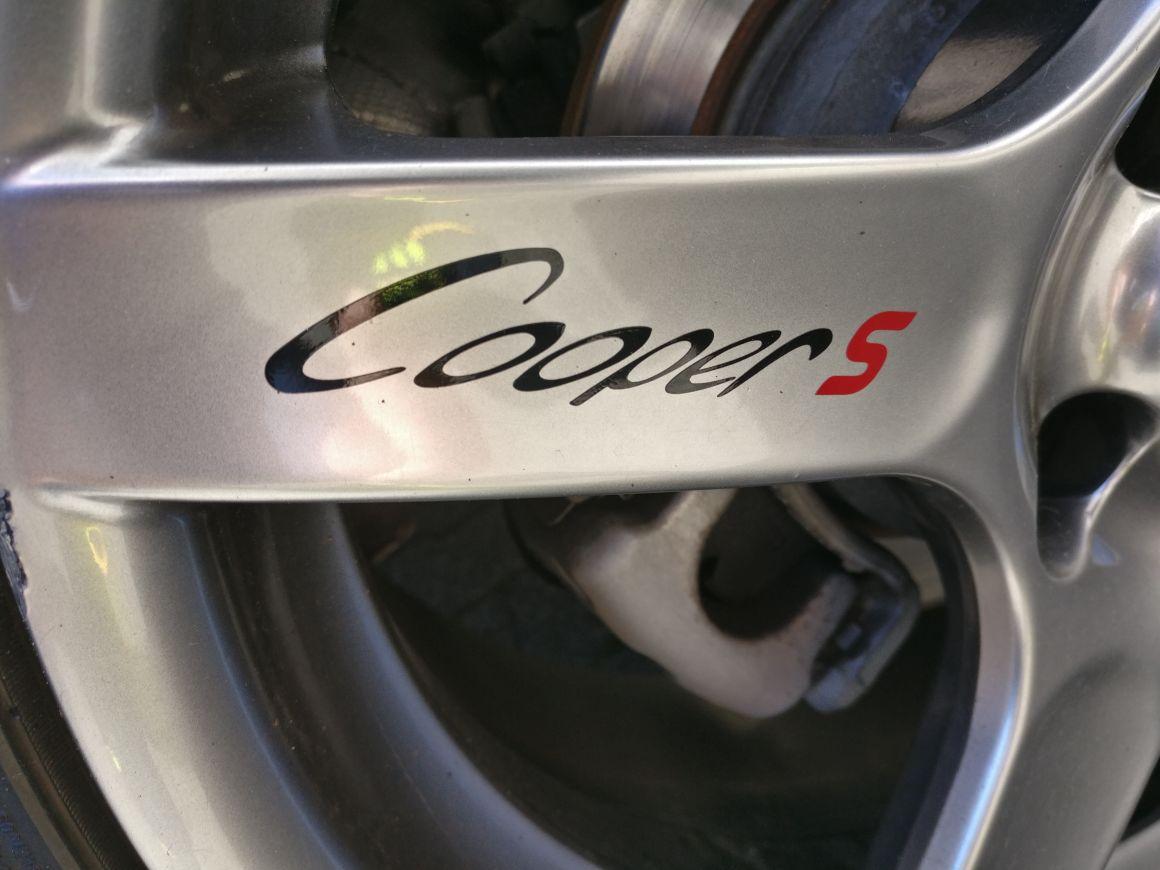
Wer kennt diese Schriftart?
ich bräuchte Eure Hilfe. Kennt jemand diese Schriftart? Sie klebt an der Felge eines Mini Cooper ...
Leider ist es mir durch die Verzerrung nicht möglich, sie durch ein Schrifterkennungsprogramm zu schicken,
deshalb bin ich auf Eure Hilfe angewiesen. Sollte es die Schriftart nicht geben, wäre mir auch mit einer
Ähnlichen geholfen!
Das sieht sehr unausgegoren aus … ich tippe auf handgeschnitzt. Das S sollte einer Satzschrift entspringen …
Aber warum nicht das Original nehmen? Das S des Originals ist schließlich sehr prägnant.
mit Hilfe der Vorlage, das Ganze nachzuzeichnen